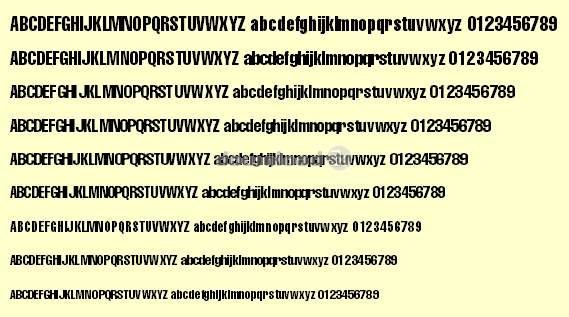
"Realist komprimierte serifenlose Schrift"
Realist komprimierte serifenlose Schrift mit einem neutralen Gefühl. Wie Helvetica Compressed. Ein Allzweck-Design, ideal für Tische, Schlagzeilen und Werbung. Schmaler als kondensierte. Präzise und deutete an, passender Font-Metriken, Standard-Zeichensatz, Kerning-Paare. Professionelle Druckqualität für Inkjet, Laser, Schriftsetzer zu 3500 dpi. Enthält 1-Studie Schriftart, senden $ 12, alle 3-Produktion Schriften erhalten.Bedarf Older versions of Mac OS require Adobe Type Manager.